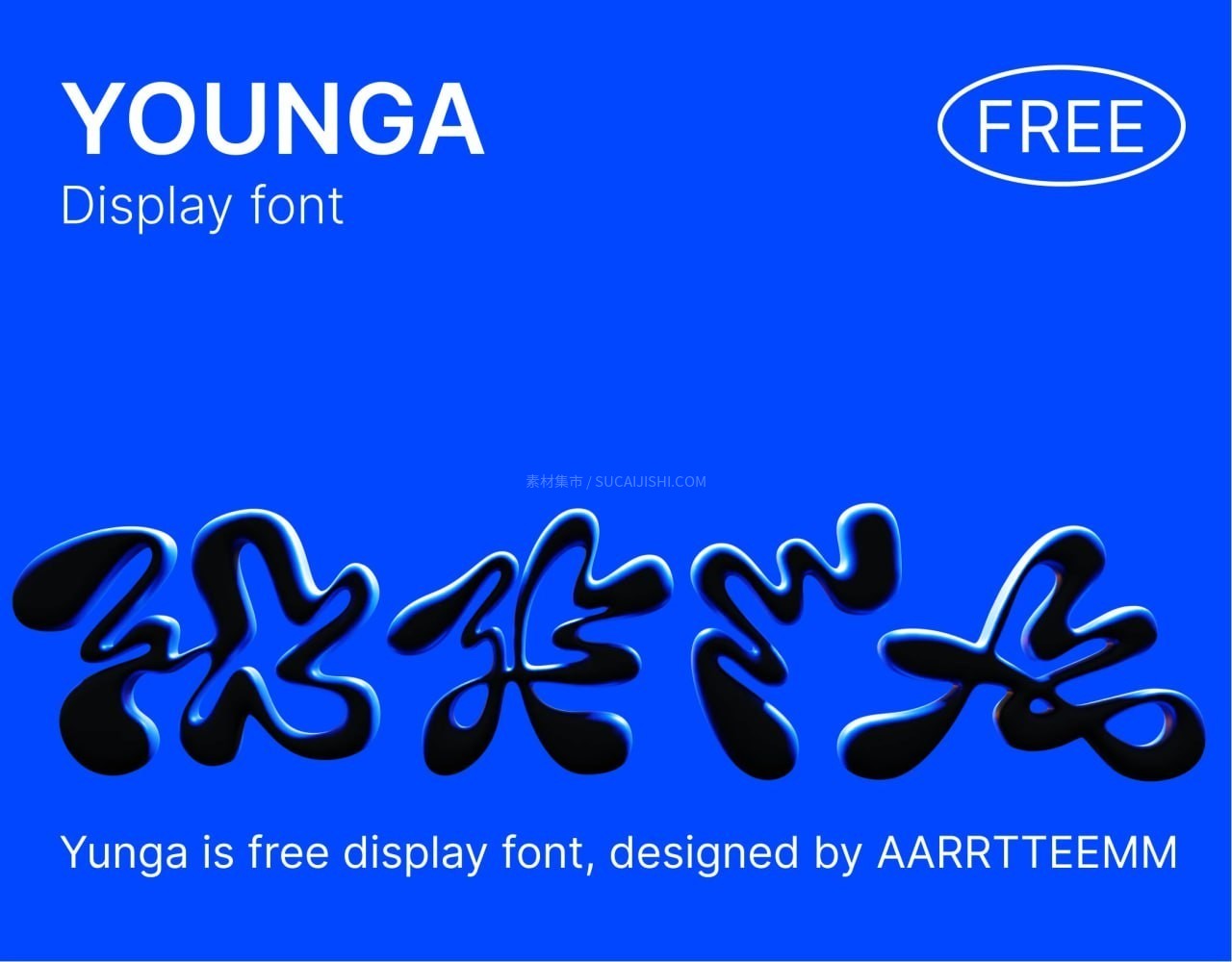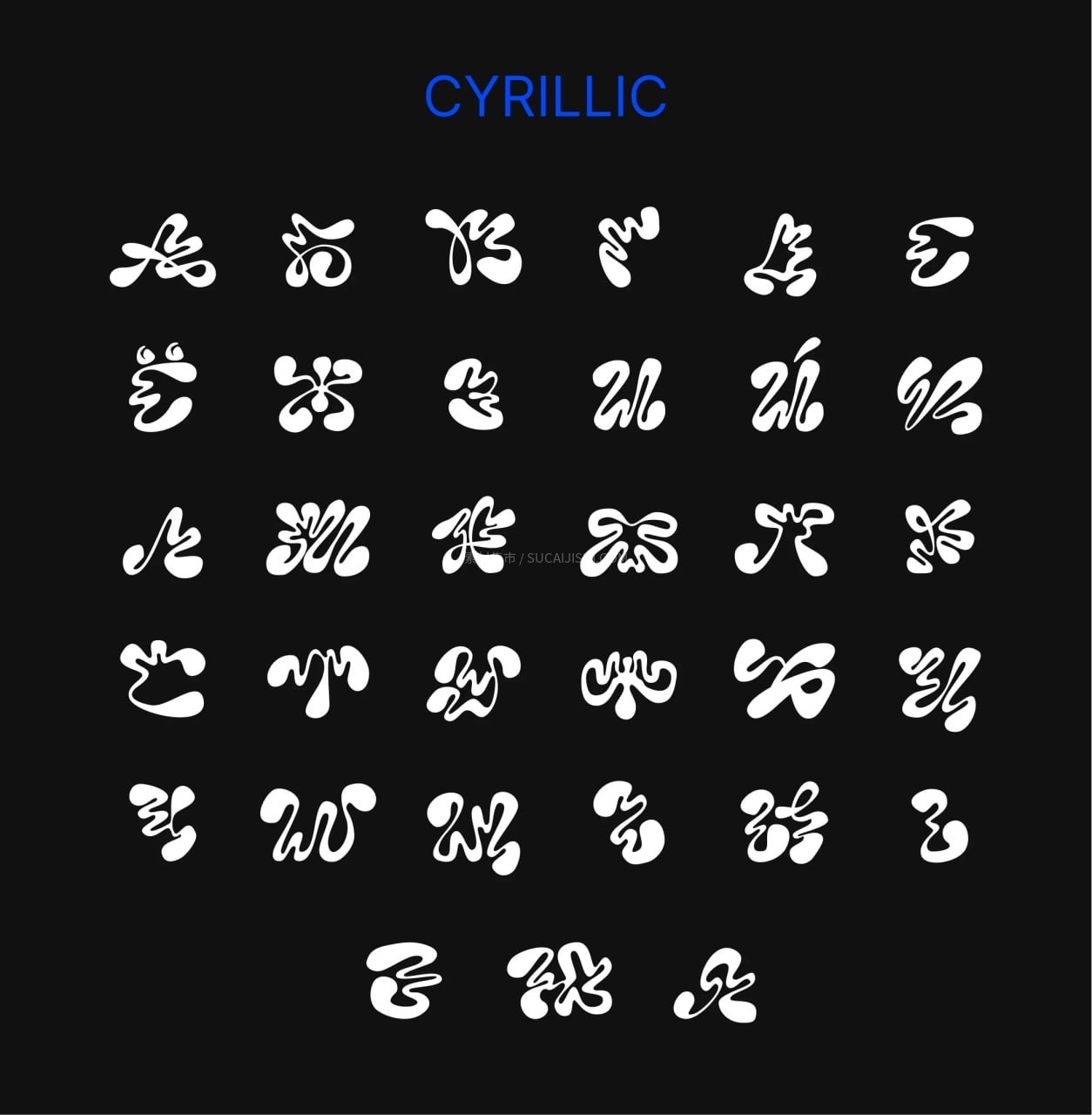
YUNGA 酸性流体艺术标题字体,免费可商用
打破常规,定义先锋!YUNGA 是一款极具视觉张力的酸性风格(Acid Graphics)英文标题字体。它融合了流体扭曲感与前卫的几何构造,呈现出一种独特的复古未来主义美学。最重要的是,这款字体授权全渠道免费可商用,无论是商业项目还是个人创作,都能为你节省版权成本,同时赋予作品顶级的设计深度与实验性色彩。